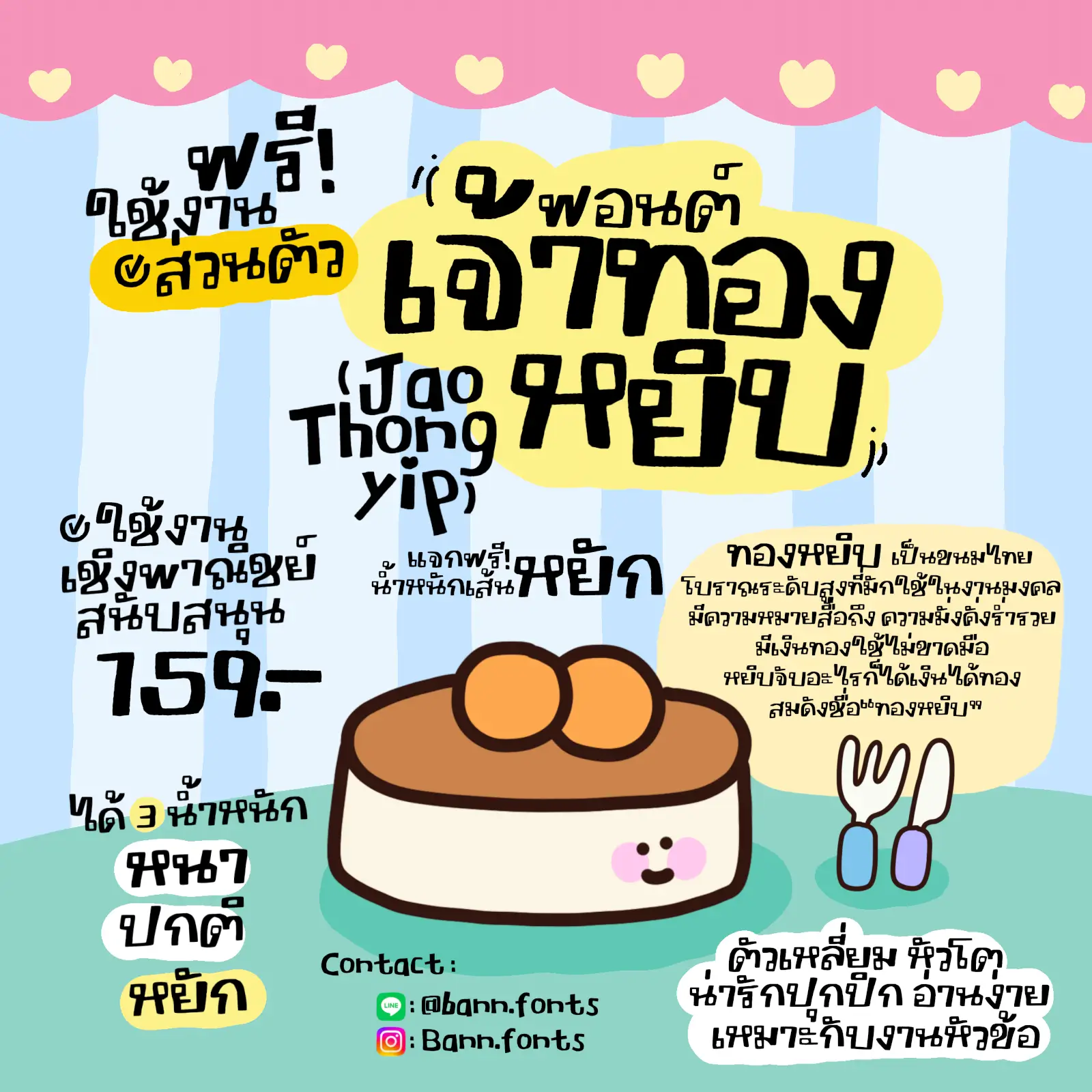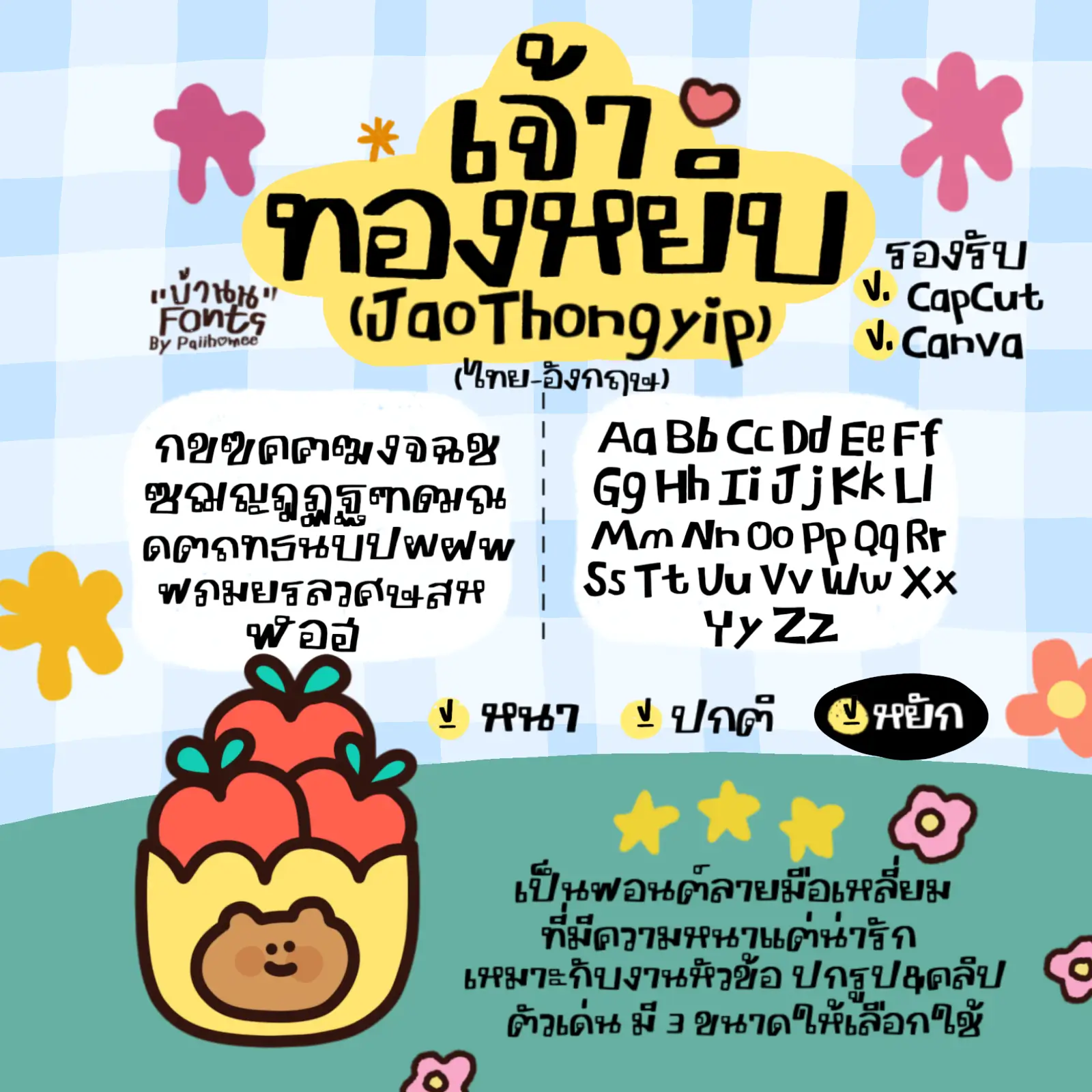
ฟอนต์เจ้าทองหยิบ – แจกให้ใช้งานฟรี สำหรับน้องๆพี่ๆ ที่ชอบฟอนต์ลายมือตัวเหลี่ยมๆ หนาๆ หัวโตๆ มีเอกลักษณ์น่าสนใจ เหมาะสำหรับงานเขียนหัวข้อ แต่งปกรูป ปกคลิป
เจ้าทองหยิบ (JaoThongyip)